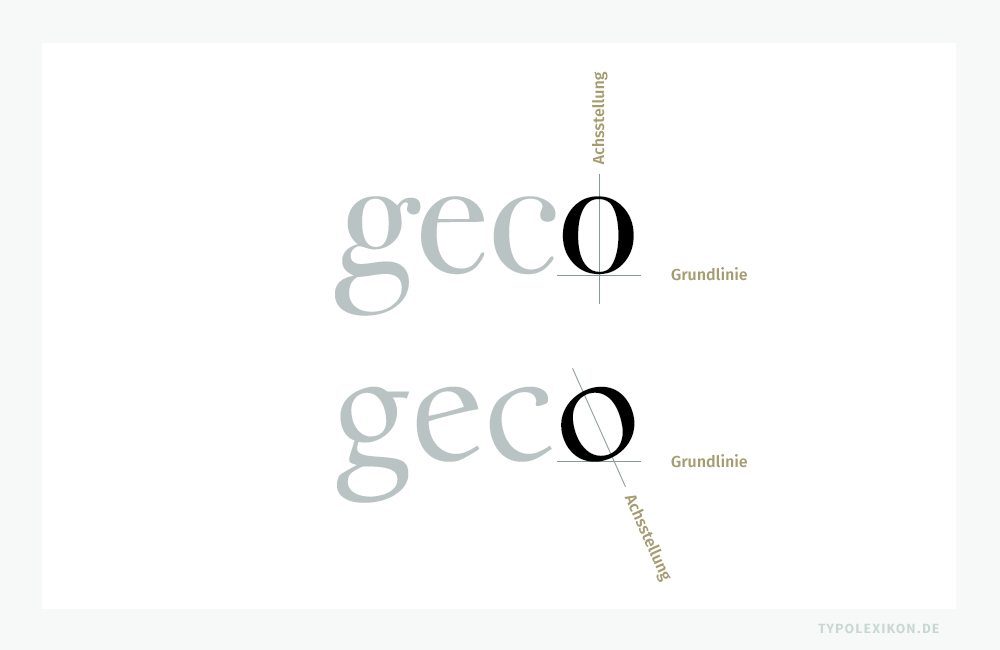
Achsstellung
»Achsstellung« ist ein Fachbegriff aus der dspr. Typografie und der Schriftgestaltung, welcher die Achsneigung runder Buchstaben – in der Regel bei Minuskeln oder der Minuskelziffer »0« – mit geschlossenen und offenen Punzen, z.B. »o«, »c«, »e« und »g«, um ihre unsichtbare horizontale und/oder vertikale Achse in Bezug auf die Grundlinie und den Mittelpunkt des Zeichens beschreibt; diagonale Abweichung von der optischen oder rechnerischen Achse eines Buchstabens
Die Achsstellung eines Buchstabens ist nicht zu verwechseln mit der Schattenachse oder einer geneigten Schriftlage, z.B. einer kursiven Schriftlage.
Die Achsstellung war ursprünglich entscheidend für die visuelle Harmonie von klassischen Drucktypen aus Metall, indem sie eine gleichmäßige Positionierung der Buchstaben ermöglichte. Bei digitalen Fonts folgt die Achsstellung ausschließlich ästhetischen Betrachtungsweisen oder der Typifikation im Rahmen der Schriftklassifikation. 1)
An der Minuskel »o« wird der Unterschied der Achsstellung zwischen einer Bodoni 72 von Dmitry Kirsanov (*1965) und einer Guardi von Reinhard Haus (*1950) sehr deutlich. Letztere ist eine Venezianische Renaissance-Antiqua, die Bodoni eine Klassizistische Antiqua.
Bei einzelnen Buchstaben bezieht sich die Achsstellung auf die Achsschiefe um die eigene Drehachse (Abweichung einer Achse von der Horizontalen oder der Vertikalen), wodurch subtile Unterschiede in Neigung und Ausrichtung entstehen. Die Achsstellung kann mit der Schattenachse eines Zeichens korrespondieren – muss aber nicht. Die Achse kann beispielsweise leicht diagonal schräg im oder gegen den Uhrzeigersinn sein, wie es bei Venezianischen Renaissance-Antiquas der Fall ist, oder senkrecht, wie es bei Vorklassizistischen Antiquas oder Klassizistischen Antiquas bevorzugt wird.
In der Schriftklassifikation spielt die Achsstellung also eine bedeutende Rolle, so auch bei der Klassifizierung zwischen Antiqua mit und ohne Serifen (Grotesk). Antiqua-Schriften mit Serifen weisen oft eine leichte Schrägstellung auf, während serifenlose Schriften eine eher aufrechte Ausrichtung zeigen.
Ein konkretes Beispiel verdeutlicht den Unterschied in der Achsstellung zwischen einer Venezianischen Renaissance-Antiqua, beispielsweise repräsentiert durch die Schriften von Nicolas Jenson (1420–1480), und einer Französischen Renaissance-Antiqua von Claude Garamond (um 1498/99–1561). Nicolas Jensons Drucktypen weisen eine subtile Schrägstellung auf, verleihend der Schrift ein dynamisches und künstlerisches Flair. Im Gegensatz dazu präsentiert die Französische Renaissance-Antiqua von Garamond eine tendenziell aufrechtere Achsstellung, was der Schrift eine Strenge und Eleganz verleiht.
Die sorgfältige Berücksichtigung der Achsstellung ist somit nicht nur ein technischer Aspekt, sondern ein künstlerisches Element, das den Charakter einer Schriftart prägt. Schriftgestalter:innen nutzen sie seit Jahrhunderten bewusst, um visuelle Nuancen zu schaffen und den Ausdruck der Schrift zu verfeinern. Diese Prinzipien halten sich bis heute in der zeitgenössischen Typografie, wo Type Designer:innen die Achsstellung als Werkzeug zur Schaffung einzigartiger und ansprechender Schriftbilder nutzen.
Die Entwicklung der Achsstellung seit der Erfindung des Buchdrucks mit beweglichen Lettern im 15. Jahrhundert durch Johannes Gutenberg (um 1400–1468) bis zur Gegenwart spiegelt die Veränderungen im polygrafischen Gewerbe, kulturellen Einflüssen und kreativen Entscheidungen von Schriftgestalter:innen wider. Während frühere Druckverfahren handwerkliche Unregelmäßigkeiten in der Achsstellung aufwiesen, ermöglichen moderne Techniken eine präzisere Kontrolle und künstlerische Freiheit bei der Gestaltung von Schriftarten.